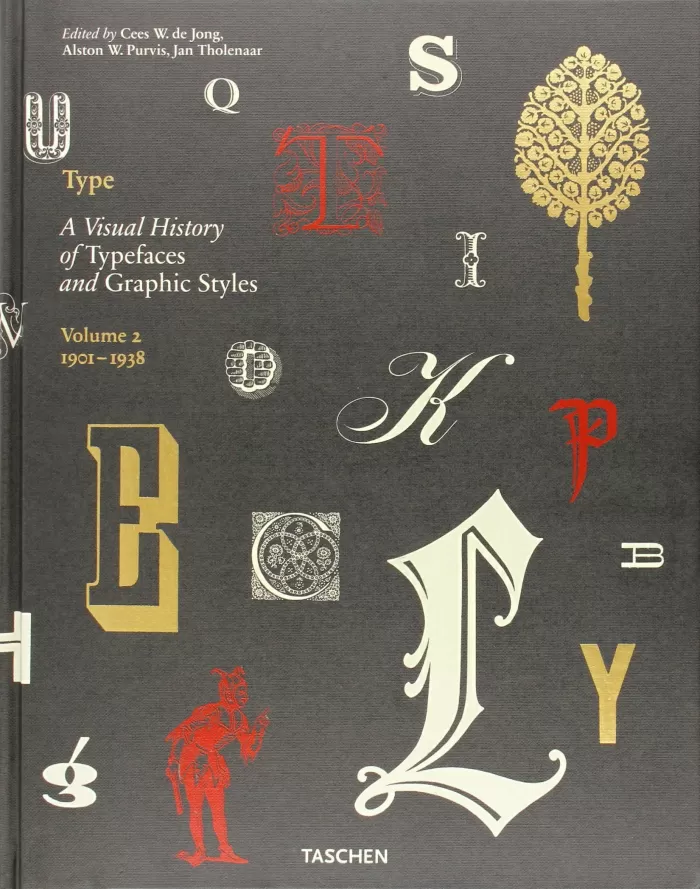
TYPE. A VISUAL HISTORY OF TYPEFACES & GRAPHIC STYLES. 1901?1938
Tipos realmente distinguidos
Una historia visual de fuentes y estilos gráficos: volumen 2
Este libro ofrece un panorama para entendidos del diseño tipográfico, explorando las fuentes más elegantes en la historia de la edición. Extraída de una distinguida colección holandesa, esta exuberante publicación en dos volúmenes sigue la evolución de la letra impresa a través de catálogos exquisitamente diseñados que muestran familias de caracteres en redonda, cursiva, negrita, seminegrita, compacta y ancha. También se incluyen filetes, florituras, capitulares y ornamentos, junto con ejemplos litográficos y letras de rotulistas, grabadores y calígrafos.
El volumen presenta obras de diseñadores tipográficos que incluyen a: William Caslon, Fritz Helmuth Ehmcke, Peter Behrens, Rudolf Koch, Eric Gill, Jan van Krimpen, Paul Renner, Jan Tschichold, A. M. Cassandre, Aldo Novarese y Adrian Frutiger.
Para dar cabida a un material tan amplio, hemos dividido este texto en dos tomos. Éste, el segundo volumen, abarca el período que va de 1900 hasta mediados del siglo XX y contiene un resumen histórico por Alston W. Purvis.